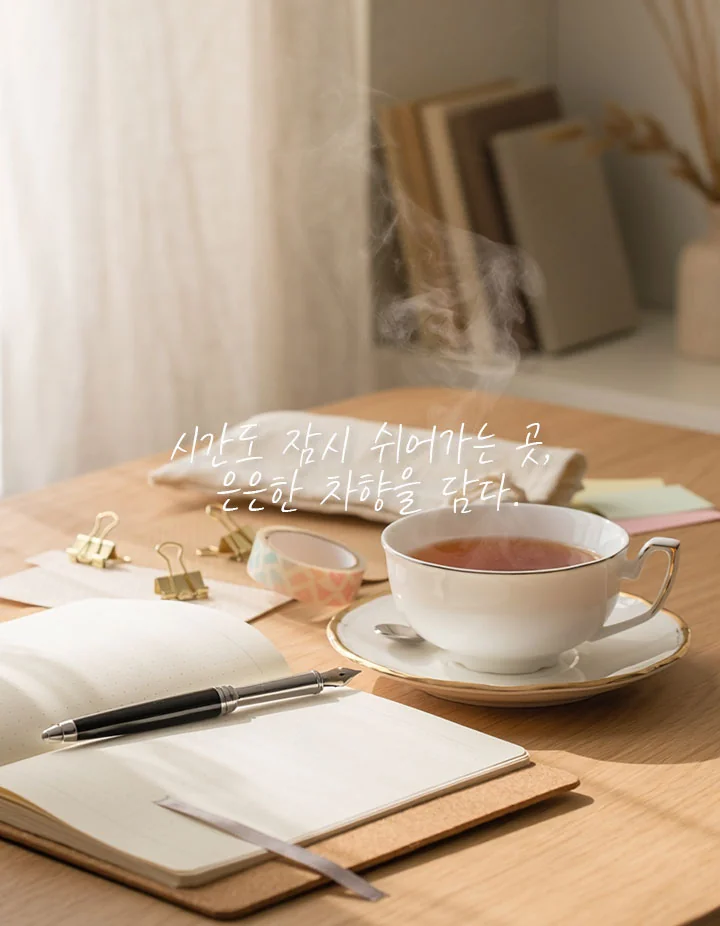
KCC은영체 — 한국저작권위원회에서 배포하는 무료 폰트입니다. 가는 펜의 방향성과 섬세한 굵기 변화가 살아 있는 자연스러운 손글씨체
한국저작권위원회가 배포하는 서체 가운데 **실제로 한 사람의 손글씨에서 나온 폰트**입니다. 2016년 위원회의 국민저작물 보물찾기 공모전에서 뽑힌 황은영 님의 글씨를 바탕으로 만들었고, 이름의 은영이 바로 그분의 이름입니다. 2017년 말에 공개됐고 폰트로 옮기는 작업은 박윤정앤타이포랩이 맡았습니다.
형태는 파일을 보고 적습니다. 이 목록에서 획이 가장 가늘어 자면을 채우는 비율이 낮고, 받침이 붙을 때 글자 높이가 달라지는 탈네모틀이며 낱자가 폭보다 높이가 커서 세로로 서 있습니다. 얇은 펜으로 또박또박 써 내려간 인상이라 편지나 엽서, 인용문처럼 개인적인 목소리가 필요한 자리에 어울립니다.
반대로 획이 가는 만큼 작은 크기나 어두운 배경에서는 뭉개지기 쉽고, 굵기가 하나뿐이라 강조를 줄 방법도 없습니다. 긴 본문이나 공식 문서에는 맞지 않습니다. 현대 한글 11,172자를 모두 담았고, 위원회 서체 가운데 드물게 웹폰트 포맷까지 공식 제공합니다.